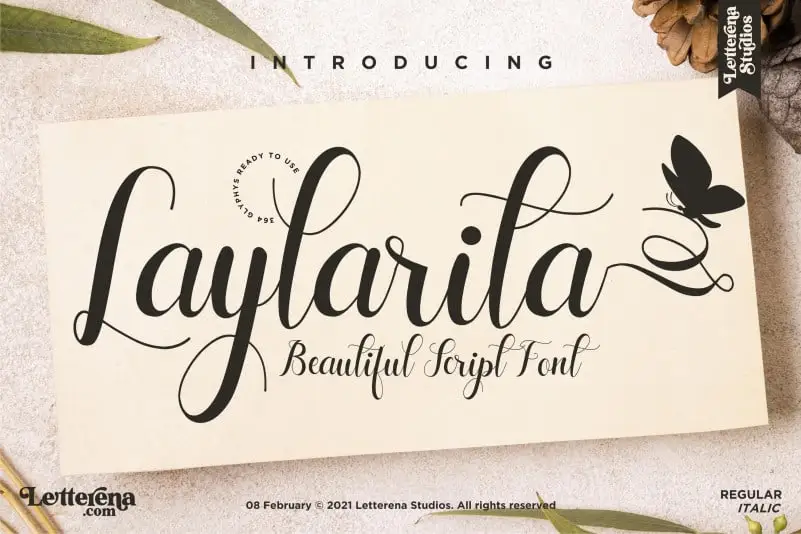
Laylarita Script Font – Download Grátis
A Laylarita Script Font é uma maravilhosa opção para quem busca uma fonte elegante para projetos diversos. Ela vem direto do designer Letterena, e oferece um toque romântico de escrita artesanal perfeito para a criação de logos, designs de embalagens ou produtos em geral, mugs, postais, etiquetas, cartões de convite, encomendas personalizadas, painéis de decoração, marcadores e até mesmo fotografias. Ideal para qualquer projeto que busque aquele charme sofisticado e delicado da escrita à mão, Laylarita Script é uma fonte perfeita para quem busca dar um toque único em seus trabalhos de design. Composta com precisão e riqueza em detalhes, essa fonte traz a beleza do script para qualquer projeto que você escolha. Sua versatilidade e elegância fazem dela uma opção primordial para designers apaixonados por criar um ar de sofisticação no seu trabalho.